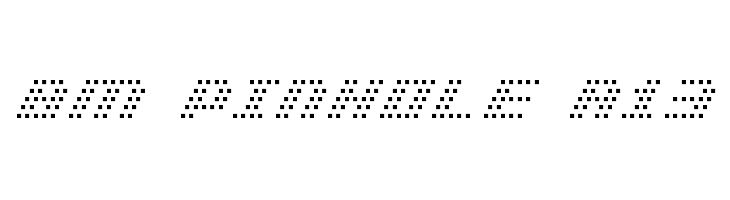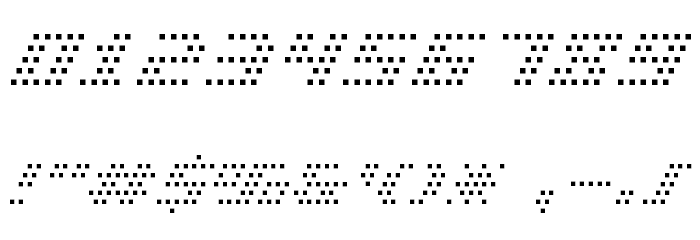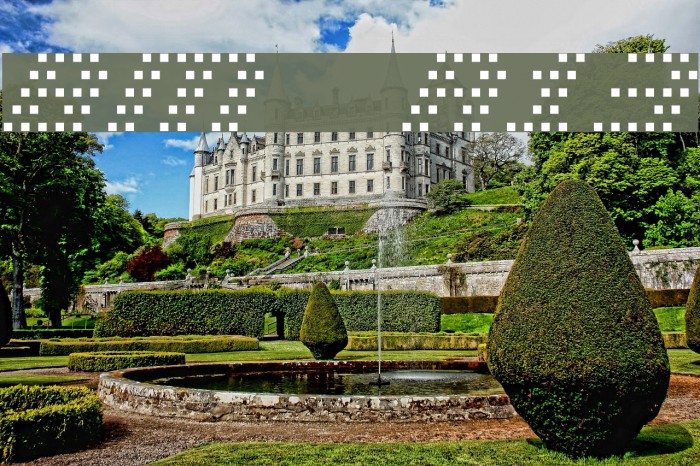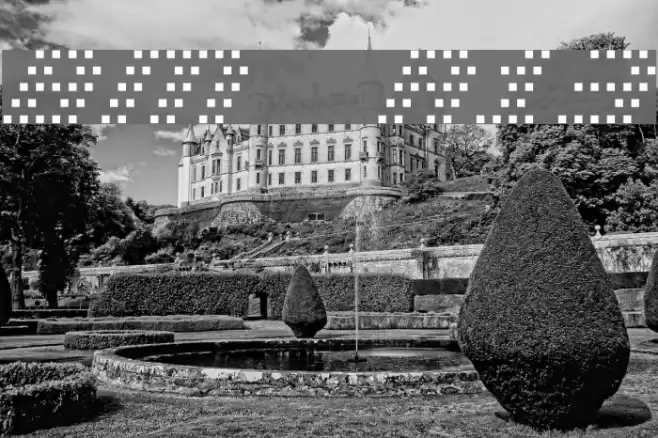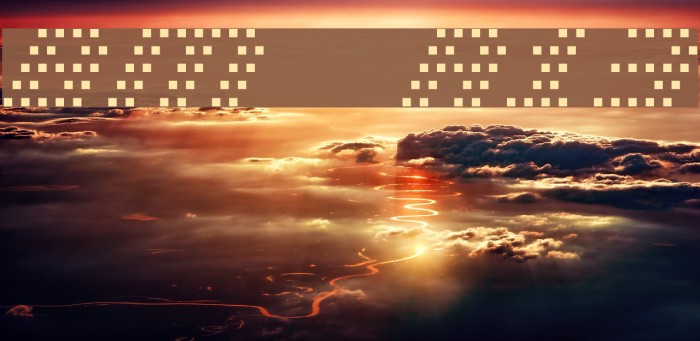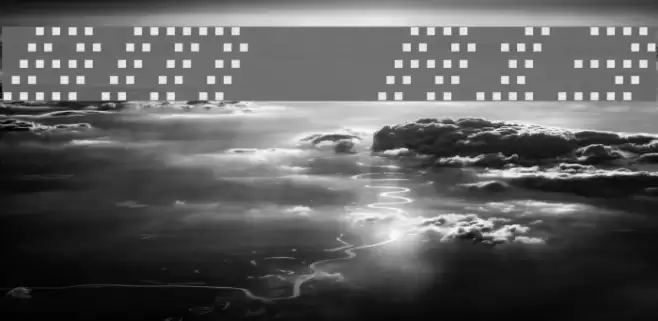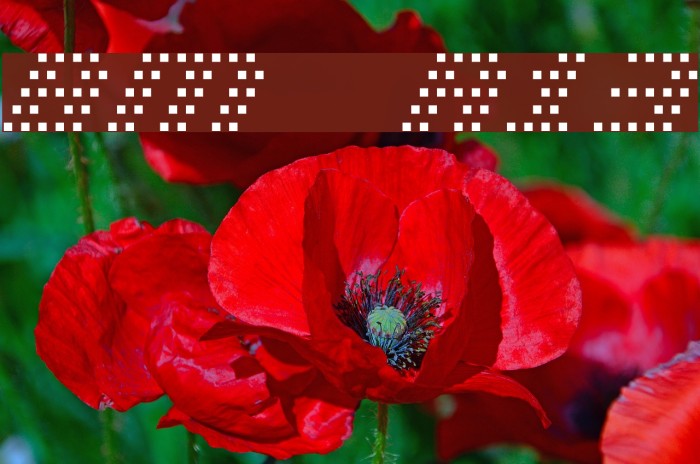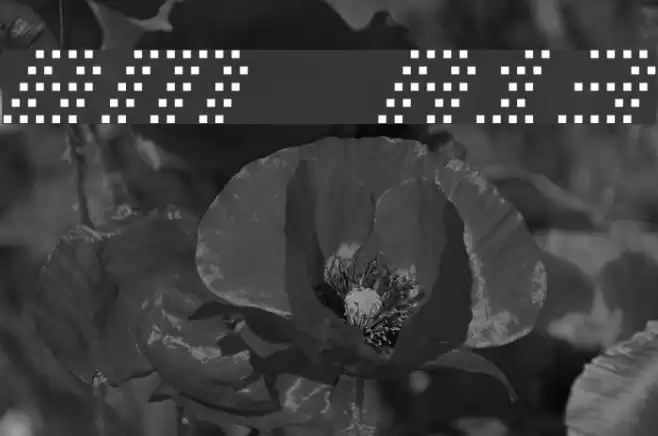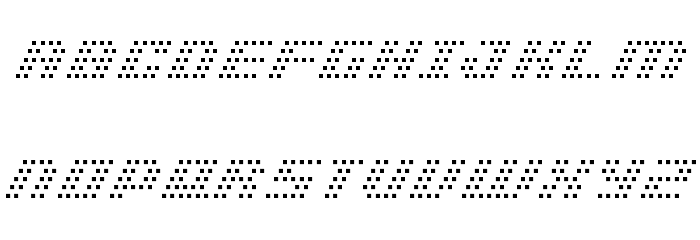
BM pinhole A13 Font
| Name | BM pinhole A13 |
| Kategorien | Pixel |
| Gesamtstil | Retro, Digital |
| Anwendungsfall | Logos, Posters, Digital Art |
| Vorgeschlagene Projekte | Ideal for digital-themed designs, retro tech projects, or any creative work that requires a unique, pixelated look. |